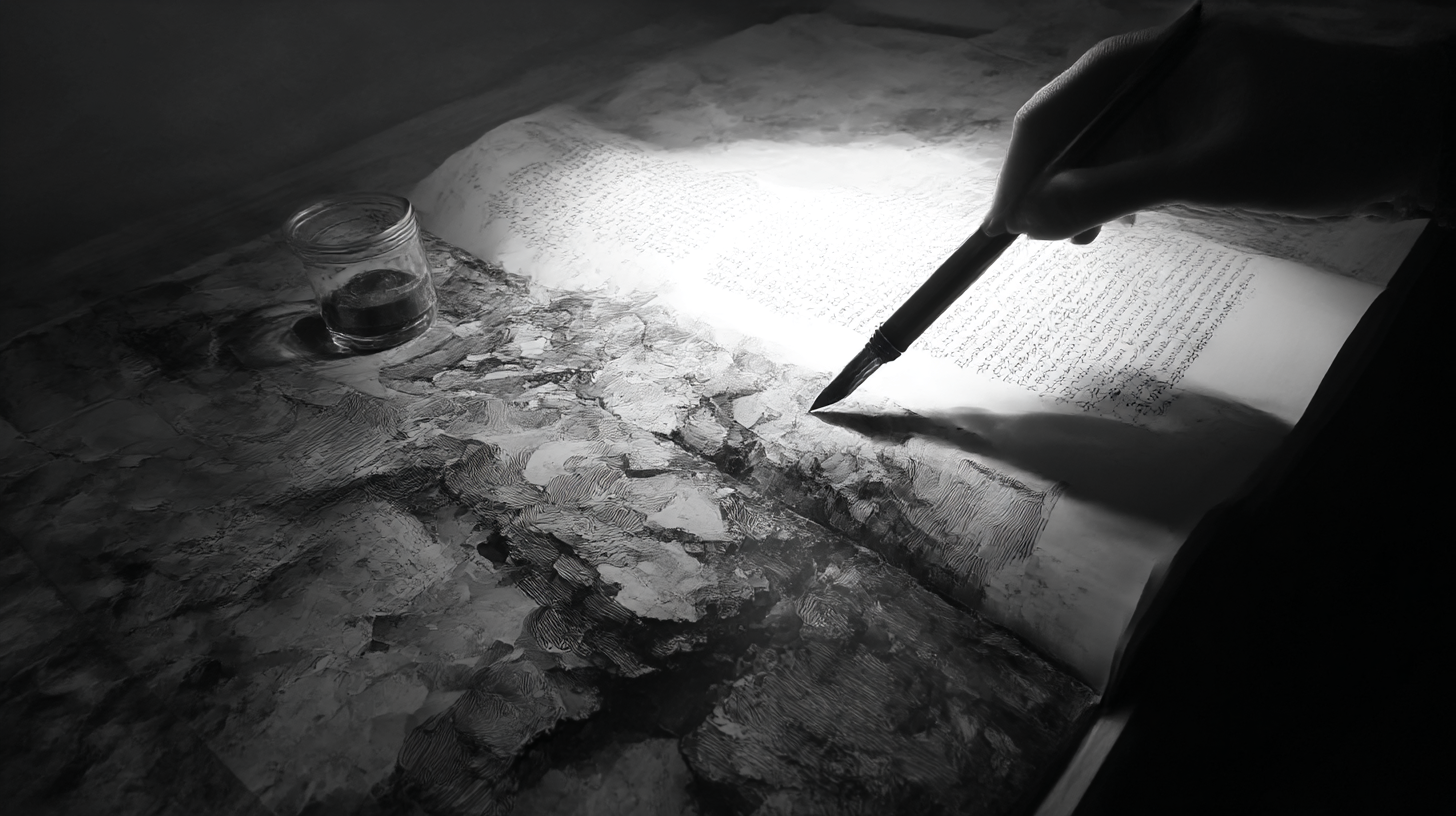
멋진 필기체 연습법 - 누구나 쉽게 따라 하기 ✍ 필기체는 단순한 글씨가 아니라, 개성을 표현하는 중요한 도구예요! 멋진 필기체를 연습하면 다이어리 꾸미기, 노트 정리, 캘리그래피 등 다양한 곳에서 활용할 수 있답니다. 🎨✨
내가 생각했을 때 필기체는 연습만 하면 누구나 멋지게 쓸 수 있는 기술이에요. 오늘은 단계별로 필기체를 쉽게 연습하는 방법을 알려드릴게요! 🖋🔥
먼저, 필기체 연습이 왜 중요한지부터 알아볼까요? 👇
📌 필기체 연습이 중요한 이유
멋진 필기체를 쓰는 것은 단순히 글씨를 예쁘게 꾸미는 것뿐만 아니라, 글을 읽기 쉽게 정리하고 필기 습관을 개선하는 데에도 큰 도움이 돼요. 🖊✨
특히 필기체 연습은 다음과 같은 장점이 있어요.
- 📖 가독성 향상 - 글씨가 깔끔해지고 보기 좋아짐
- 🧠 기억력 향상 - 손으로 직접 쓰면서 학습 효과 극대화
- 🎨 개성 표현 - 나만의 필기 스타일로 감성적인 필기 가능
- 📝 노트 정리 용이 - 필기 속도가 빨라지고 정리력이 향상됨
📊 필기체 연습 전후 비교
구분 연습 전 연습 후 글씨 형태 불규칙하고 삐뚤어짐 일정한 크기와 균형 유지 속도 느리고 자주 끊김 자연스럽고 부드러운 흐름 가독성 읽기 어려운 경우 많음 깔끔하고 쉽게 읽을 수 있음 이처럼 필기체 연습을 하면 가독성과 속도가 동시에 향상될 수 있어요. ✍🔥 이제 다양한 필기체 스타일을 알아볼까요? 🎨
✍ 필기체 스타일 종류
필기체는 스타일에 따라 분위기가 달라지고, 활용할 수 있는 용도도 다양해요! 어떤 필기체를 연습할지 고민된다면, 아래에서 대표적인 필기체 스타일을 비교해보고 나에게 맞는 스타일을 선택해보세요. 😊
📌 대표적인 필기체 스타일 비교
필기체 스타일 특징 추천 용도 🖊 정자체 획이 일정하고 단정한 글씨체 노트 정리, 시험 답안 🖋 흘림체 획이 부드럽게 연결되는 스타일 다이어리 꾸미기, 캘리그래피 ✏ 둥근 글씨체 귀엽고 부드러운 느낌의 글씨체 일기, 메모 🖌 캘리그래피 스타일 필압 조절로 강약이 있는 글씨체 명언 필기, 카드 꾸미기 필기체 스타일은 본인의 필기 습관과 목적에 맞춰 선택하는 것이 중요해요! 이제 필기체 연습을 시작하기 전에 알아야 할 기본 원칙을 살펴볼까요? ✨
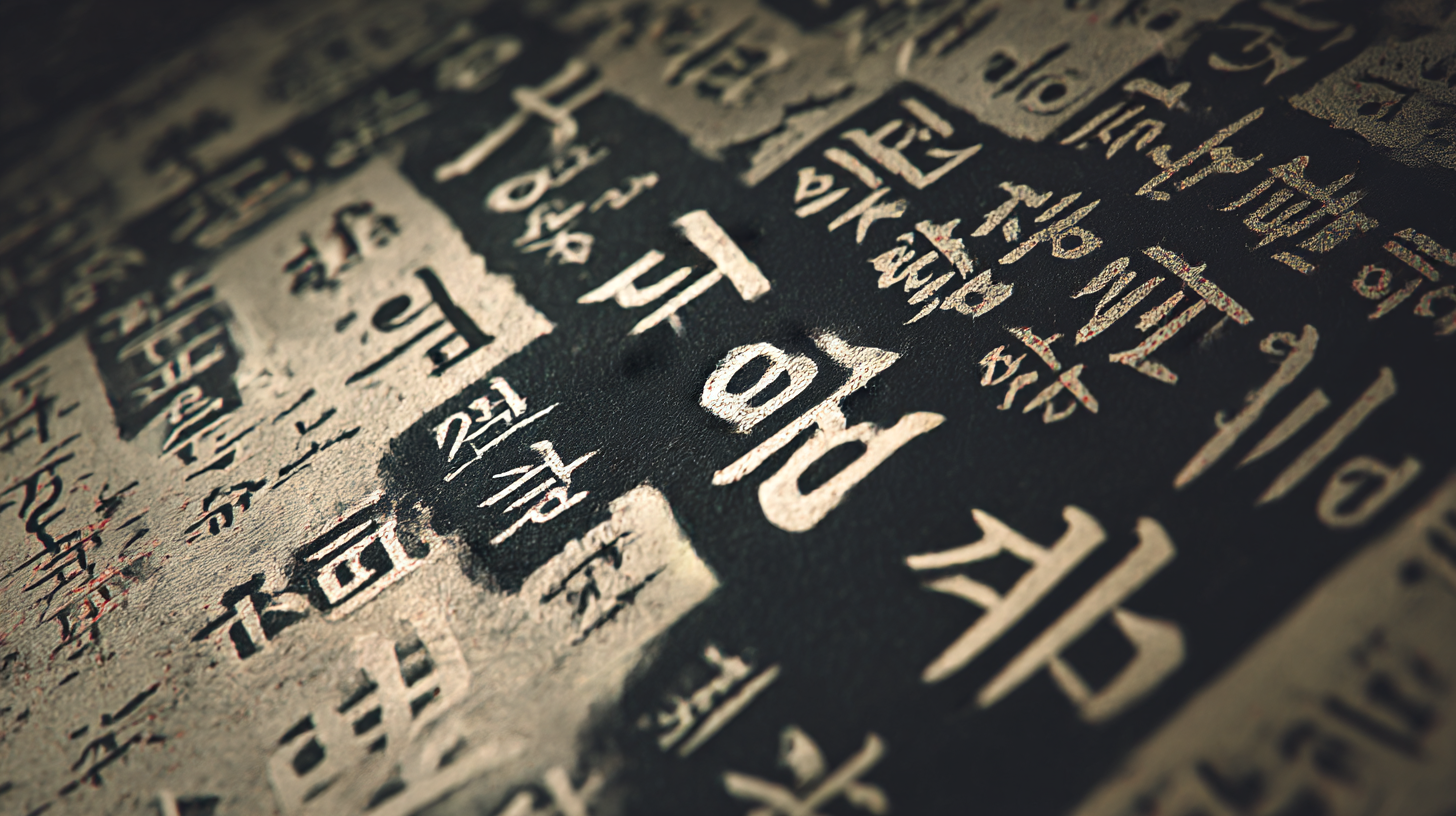
필기체 스타일 종류 📖 필기체 연습을 위한 기본 원칙
멋진 필기체를 쓰기 위해서는 일정한 연습과 몇 가지 기본 원칙을 지키는 것이 중요해요! 손글씨는 연습하면 점점 개선될 수 있기 때문에, 꾸준히 연습하는 것이 가장 중요하답니다. ✍✨
✅ 필기체 연습할 때 꼭 지켜야 할 5가지 원칙
원칙 설명 1. 일정한 글자 크기 유지 모든 글자가 균일한 크기를 가지도록 신경 쓰기 2. 필기 속도를 천천히 조절 너무 빠르게 쓰지 말고, 획을 또박또박 쓰는 연습 3. 자간과 행간 맞추기 글자 간격을 일정하게 유지해 가독성을 높이기 4. 손의 힘 조절 연습 필압을 조절해 획의 강약을 자연스럽게 표현 5. 반복적인 연습 꾸준한 연습이 가장 중요한 요소! 이 기본 원칙을 지키면서 연습하면 자연스럽게 멋진 필기체를 완성할 수 있어요! 🎨 이제 본격적으로 단계별 필기체 연습법을 시작해볼까요? ✨
📜 단계별 필기체 연습법
필기체 연습은 기본적인 선 연습부터 시작해 점점 난이도를 높여가는 방식이 효과적이에요! 아래 단계를 차근차근 따라 하면 누구나 쉽게 멋진 필기체를 완성할 수 있답니다. ✍✨
📌 필기체 연습 4단계
단계 연습 내용 설명 1단계 기본 획 연습 직선, 곡선, 점선 등 다양한 선을 일정하게 그려보기 2단계 알파벳 & 한글 연습 각 글자의 균형을 맞추면서 또박또박 써보기 3단계 단어 연결 연습 필기체의 자연스러운 흐름을 익히기 위해 단어를 연결해서 쓰기 4단계 문장 쓰기 연습 긴 문장을 써보면서 일정한 필기 스타일 유지하기 이 단계를 따라 하면 자연스럽게 필기체가 안정되고, 손글씨 스타일이 멋지게 변할 거예요! 🎨 이제 필기체 연습에 도움이 되는 필기구 추천도 함께 살펴볼까요? 🖊
필기체 연습을 할 때는 잉크 번짐이 적고, 필기감이 부드러운 펜을 사용하는 것이 좋아요! 또한, 적절한 노트를 선택하면 글씨 연습이 더욱 편리해진답니다. ✨
노트 종류 특징 추천 필기체 모눈 노트 균형 잡힌 글씨 연습 가능 정자체 도트 그리드 노트 획 정렬에 도움을 줌 흘림체 무지 노트 자유로운 필기 가능 캘리그래피 필기구와 노트를 잘 선택하면 연습 과정이 훨씬 즐거워질 거예요! 이제 필기체를 더 예쁘게 쓰는 실전 꿀팁도 함께 알아볼까요? ✨
💡 필기체를 예쁘게 쓰는 실전 꿀팁
멋진 필기체를 완성하려면 단순한 반복 연습뿐만 아니라 몇 가지 핵심 포인트를 신경 쓰는 것이 중요해요! 작은 습관을 바꾸는 것만으로도 훨씬 정돈된 글씨를 쓸 수 있답니다. ✍✨
📌 필기체를 더욱 예쁘게 만드는 5가지 팁
꿀팁 설명 1. 일정한 글자 크기 유지 모든 글자의 높이와 너비를 일정하게 맞추면 훨씬 깔끔한 글씨가 완성돼요. 2. 글자 간격 & 행 간격 맞추기 자간(글자 간격)과 행 간격을 적절히 유지하면 가독성이 높아져요. 3. 손목의 힘 빼기 손목에 힘이 들어가면 필기가 뻣뻣해질 수 있어요. 부드러운 필기를 위해 손목을 자연스럽게 움직이세요. 4. 필기 속도를 조절 너무 빠르게 쓰면 글씨가 흐트러질 수 있어요. 처음엔 천천히 연습하고 점점 속도를 올려보세요. 5. 손글씨 가이드 활용 모눈 노트나 도트 그리드 노트를 활용하면 글씨를 일정하게 정리하는 데 도움이 돼요. 이 팁들을 적용하면 더욱 감각적이고 정돈된 필기체를 완성할 수 있어요! 🎨 이제 필기체 연습과 관련된 자주 묻는 질문(FAQ)을 확인해볼까요? 🤔
Q1. 필기체 연습을 하루에 얼마나 해야 효과적인가요?
A1. 하루 10~15분 정도 꾸준히 연습하는 것이 좋아요! 짧더라도 매일 연습하면 손글씨가 자연스럽게 발전한답니다. ✍✨
Q2. 필기체를 연습할 때 어떤 노트를 사용하는 것이 좋을까요?
A2. 모눈 노트나 도트 그리드 노트를 사용하면 글자 정렬이 쉬워서 연습에 도움이 돼요. 자유로운 필기를 원한다면 무지 노트도 추천해요! 📒
Q3. 필기체가 삐뚤어지는 것을 방지하려면 어떻게 해야 하나요?
A3. 줄이 있는 노트를 활용하고, 손목에 힘을 빼면서 천천히 써보세요. 처음에는 연필로 가이드라인을 그린 후 따라 쓰는 것도 좋은 방법이에요. 🖊
Q4. 필기체 속도를 높이고 싶은데 어떻게 하면 좋을까요?
A4. 먼저 천천히 글씨의 균형을 잡는 연습을 한 후, 점점 속도를 올려보세요. 한꺼번에 속도를 올리기보다는 단계별 연습이 중요해요! ⏳
Q5. 글씨가 너무 작거나 크면 어떻게 조절할 수 있나요?
A5. 모눈 노트나 도트 노트를 활용해 일정한 크기의 글씨를 연습하는 것이 좋아요. 또한 손글씨 가이드 라인을 참고하며 연습하면 효과적이에요! 📏
Q6. 손이 떨려서 글씨가 고르지 않아요. 어떻게 하면 좋을까요?
A6. 손목의 힘을 너무 주지 말고, 편안한 자세로 필기하는 것이 중요해요. 또한, 처음에는 천천히 또박또박 쓰는 연습을 해보세요. 🎨
Q7. 디지털 필기체 연습도 효과가 있을까요?
A7. 네! 태블릿이나 디지털 노트를 활용해 연습하면 손글씨 스타일을 디지털에서도 동일하게 유지할 수 있어요. 하지만 처음에는 종이에 쓰는 연습이 더 효과적이에요. 💻✍
Q8. 필기체를 더 감성적으로 꾸미는 방법이 있을까요?
A8. 캘리그래피 스타일을 적용하거나, 컬러펜을 활용해 포인트를 주는 것도 좋아요. 또한, 글씨에 리듬감을 주면서 쓰면 더욱 멋진 필기체가 완성된답니다! 🎨🖌